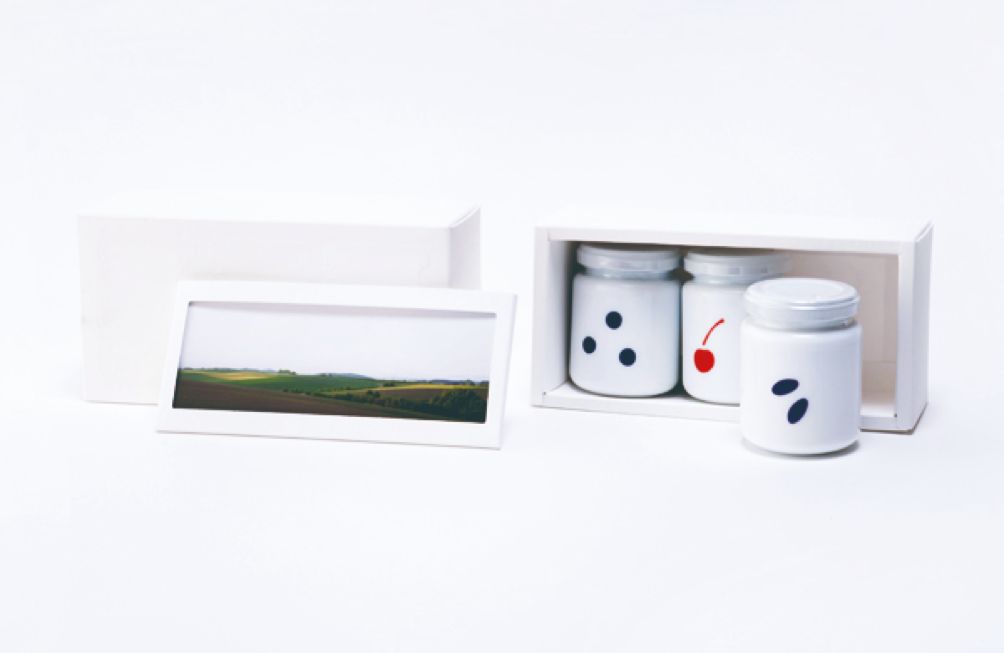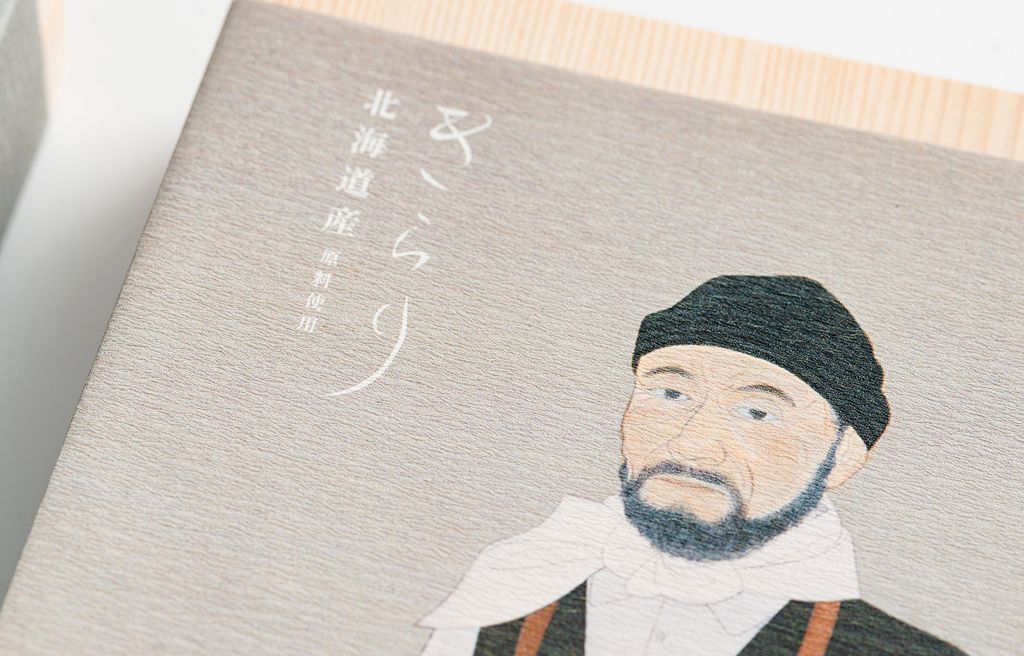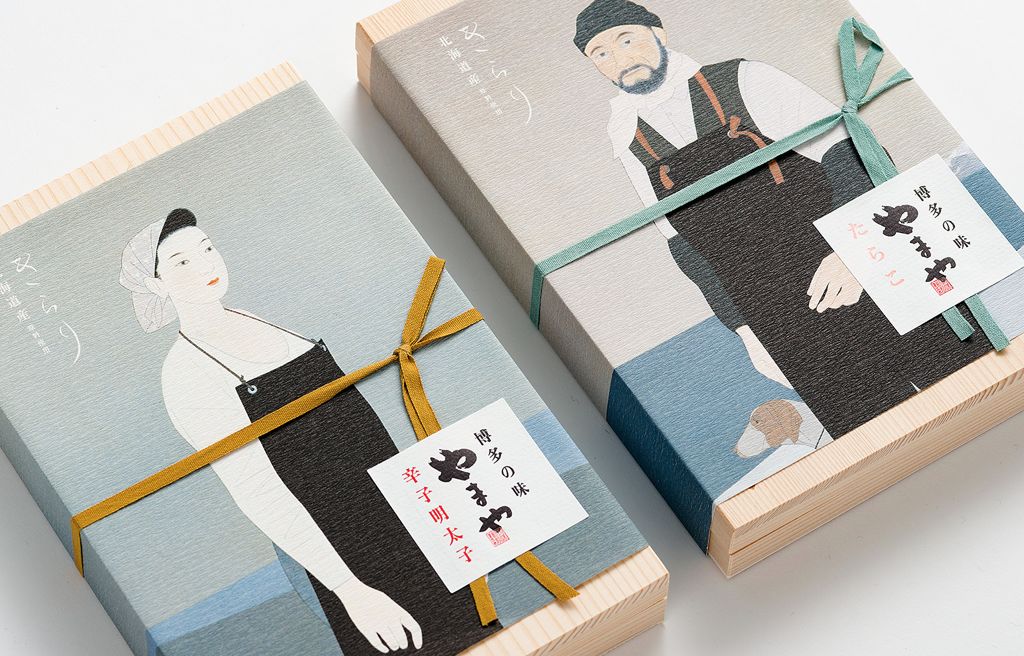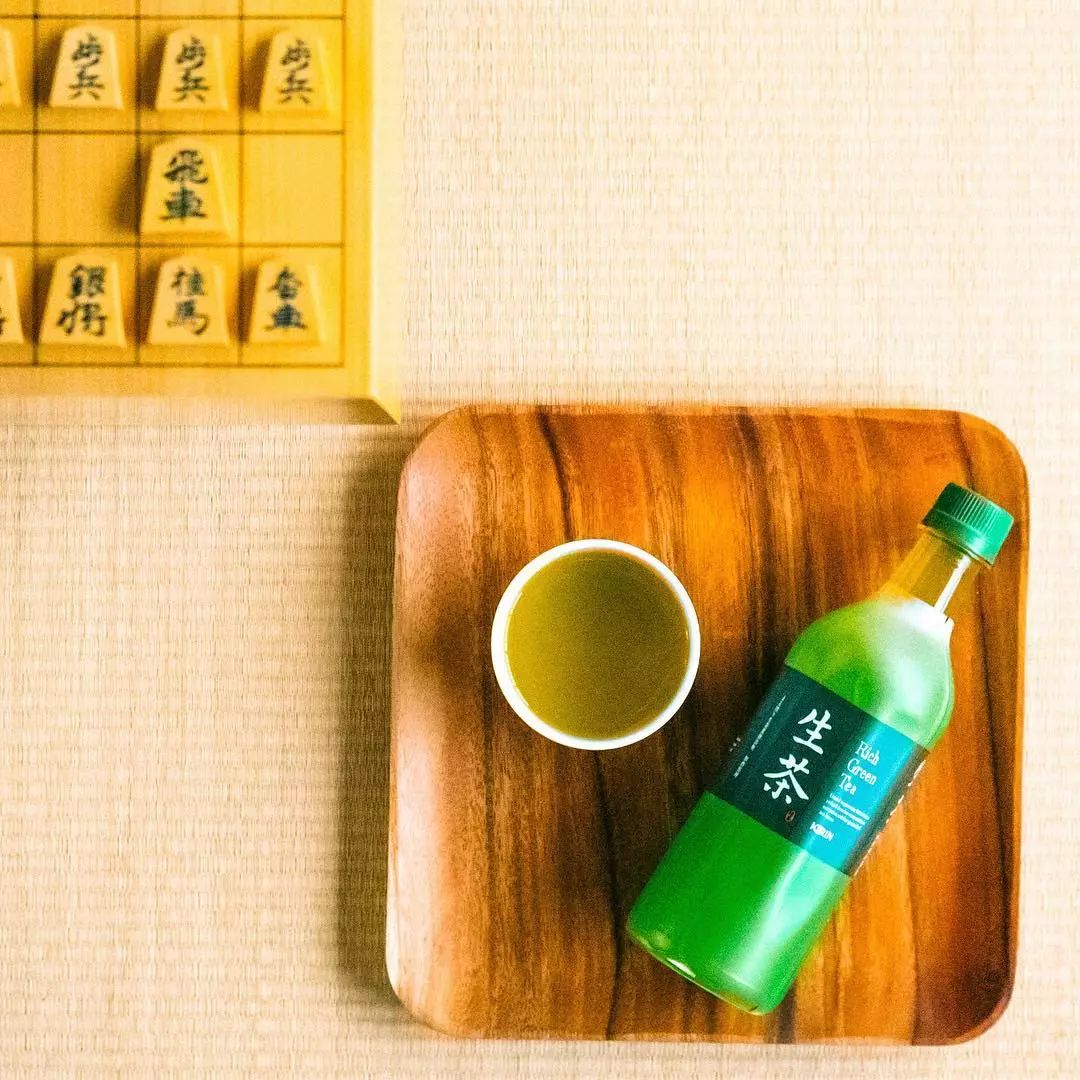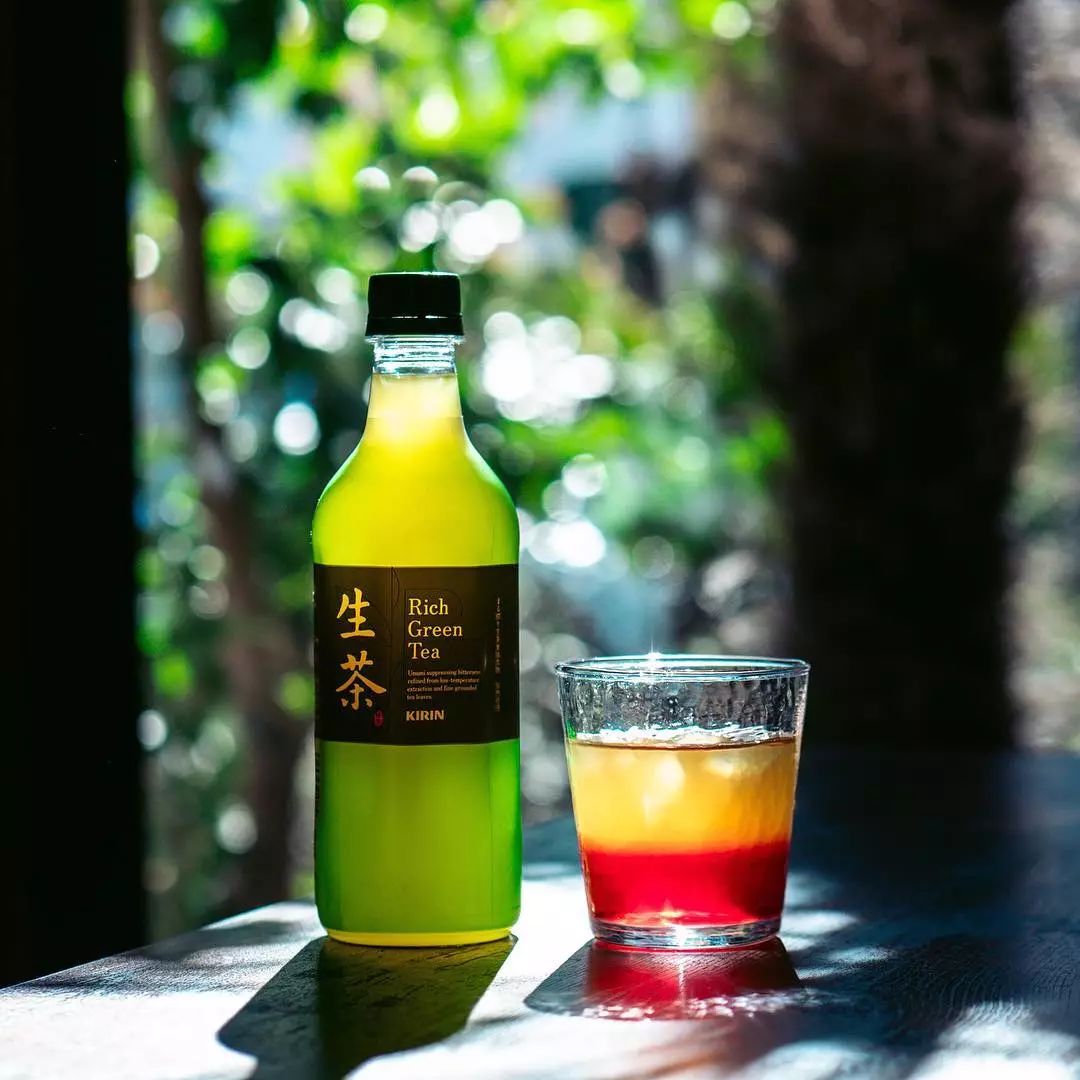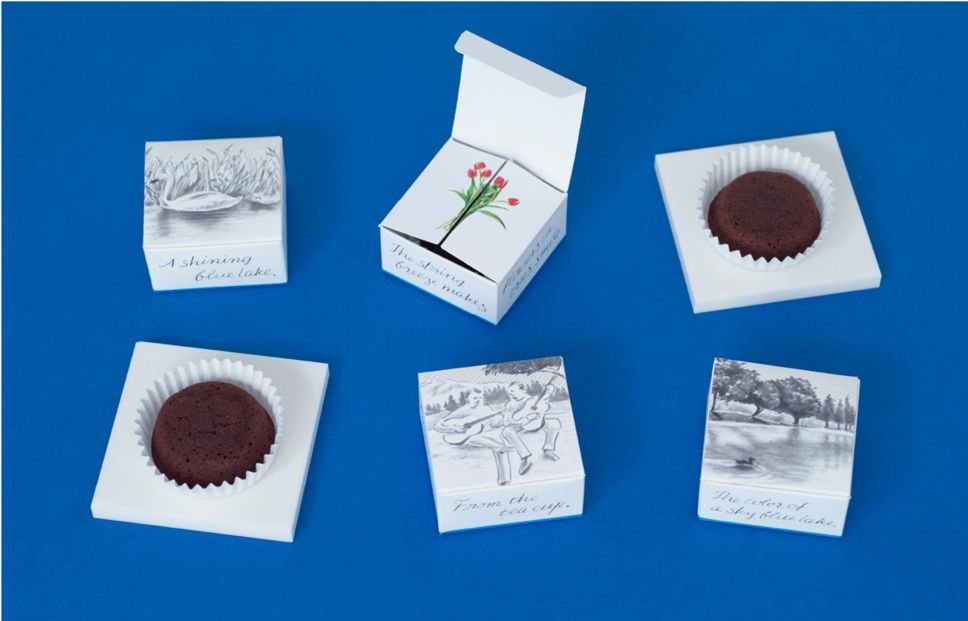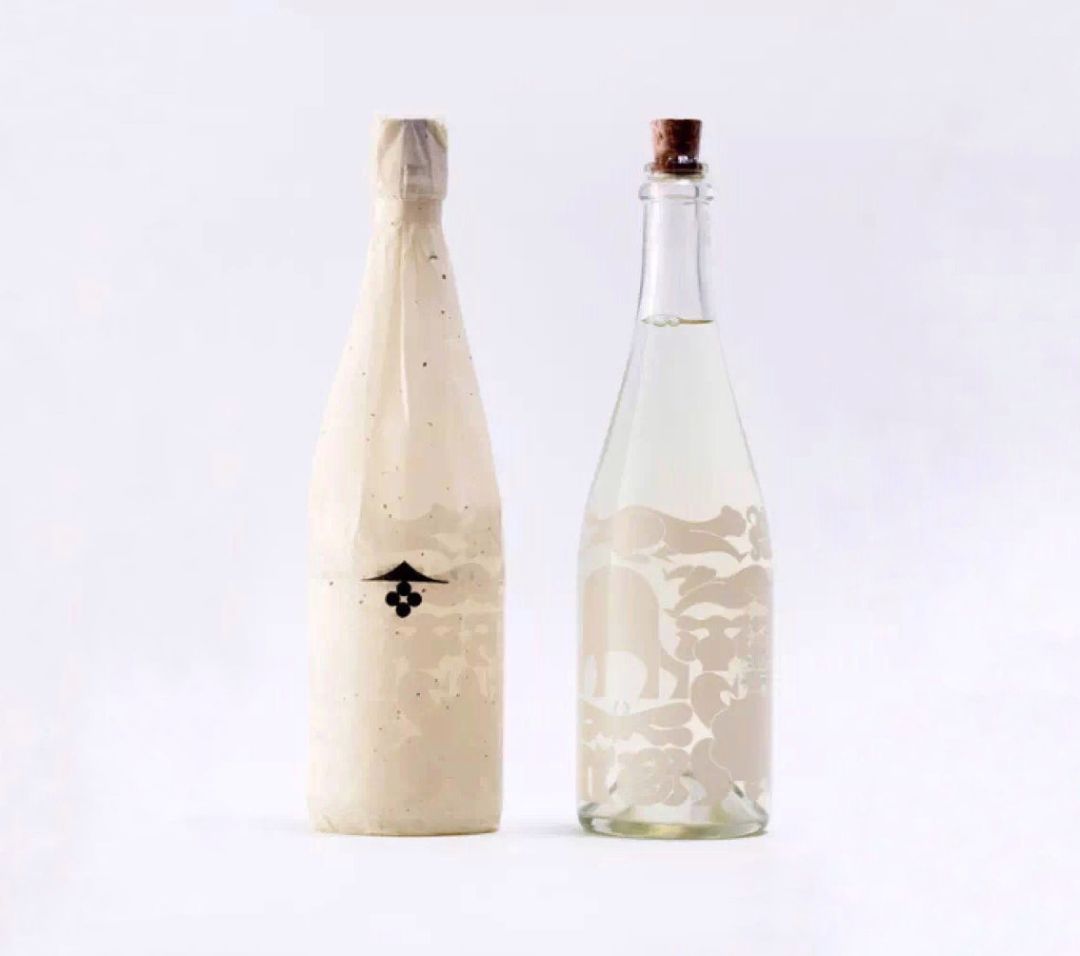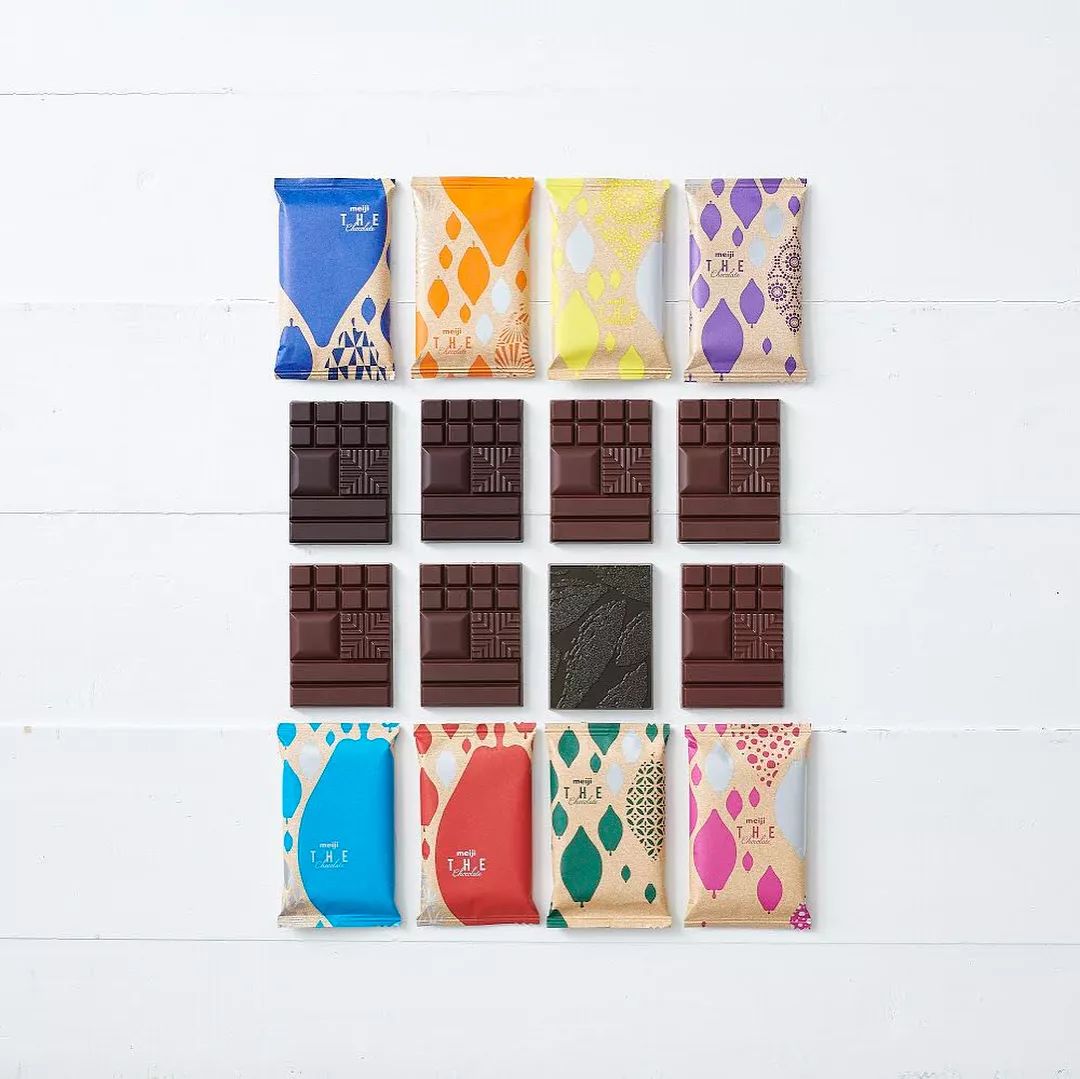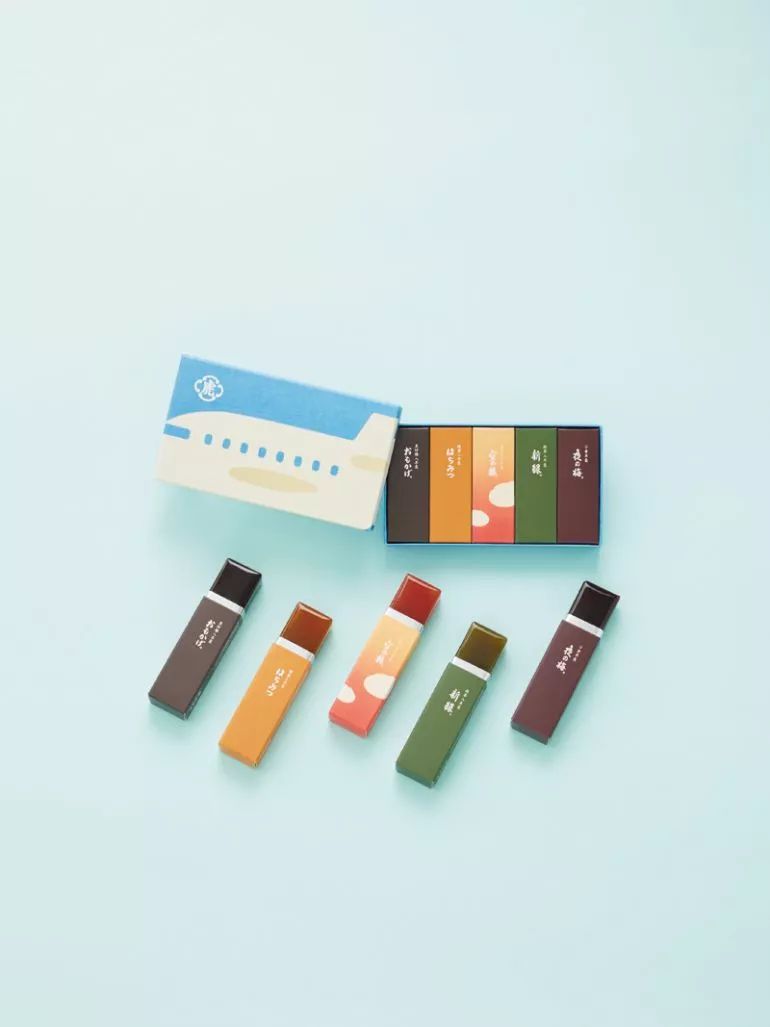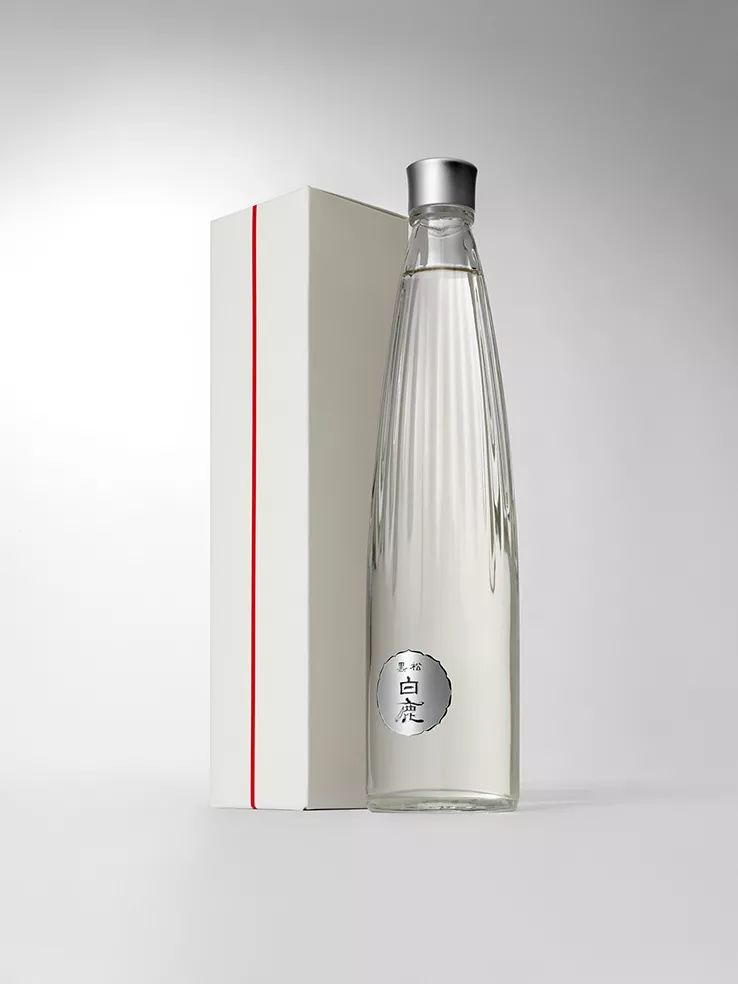
日本最美包装大赏:有些零食,负责好看就够了
说到小时候最爱的香菇肥牛和咪咪虾条,和咸咸淡淡的味道一起涌上心头的,往往还有外面那一层薄薄的包装。尽管我们被越来越多的物品包围,“包装”却是这个故事里不变的开端。一个足够美好的包装,不仅会道出商品的价值,打开它时窸窸窣窣的声音、光滑或粗糙的手感、视觉上的感触,更会化为记忆留存。
今天想和大家分享一个有关包装的大奖——1985年以来,日本包装设计协会(JPDA)每两年一次颁发设计大奖,奖励那些在商品过剩的年代里,脱颖而出的包装。让我们先从人人都爱的零食看起吧🍬
YAMAYA きらり辛子明太
2013
福冈的辣味明太子品牌Yamaya的招牌产品,精选北海道喷火湾的阿拉斯加鳕卵,属明太子中的上品。北海道的插画师蓬田康弘在包装上细致地描绘出了品牌创始人山本夫妇围着围裙的形象。
简洁的木盒和沉静的色调令人联想起大海,凸显出产品的鲜度和高级感,而插画又令人追忆起品牌的原点——来自一个日式家庭厨房的温暖心意。
美瑛果酱
2019
北海道美丽的农业之町美瑛出产的果酱,不同于大多数果酱“土特产风格”的包装,简洁的白色罐体敢于删去多余信息,这源于对果酱本身的品质足够自信,在吃完之后也有诸多循环使用的可能性。
而包装盒本身则变为相框——“本品建议搭配产地风景一并食用”。这款包装也获得了2018年的Good Design赏。
宝塚牛乳
2015
兵库县的人气牛奶屋宝塚的招牌包装,设计师植松达马从众多的红色中选出了不易过时的一种,配合圆乎乎的玻璃瓶,贴合我们小时候对牛奶的亲切记忆。
Logo仅仅是两个简洁的圆圈,以线条的细微变化唤起与生产者的联结,组成无添加、无调整牛奶的安心形象。
KIRIN 生茶
2017
遍地都是自动贩卖机的日本,茶类饮料更是战国中的战国,麒麟(KIRIN)却凭着2016年升级后的「生茶」脱颖而出。因为太火,甚至为此开出了专门的Ins账号。其中的秘诀除了低温萃取、抑制苦涩的好味道,更少不了设计上的功夫。
这款包装的设计指导福泽卓马是2018年JAGDA的新人赏得主(🔍点击回顾)。圆润的瓶子有哑光质感的表面,半透明的抹茶色衬托了茶汤的鲜度,减少了塑料瓶的“速食感”。因为这份简洁,反而老远就能自动售货机眼花缭乱的选项里辨别出来。
RURU MARY'S 巧克力
2019
巧克力集团Mary Chocolate的新品牌,包装由2016年JAGDA新人赏的获得者川上惠莉子操刀,在少女感和贵妇感之间取得了平衡。随着打开盒子,浅淡的素描风景里跃出花植的色彩,作为收尾的巧克力显得稳重又好吃😋
资生堂╳醉仙酒造 纯米大吟酿
2019
资生堂跨界做清酒?这样的说法并不全对。这款清酒源于资生堂2011年日本东山大地震后的复兴支援计划。资生堂的两位创意人——艺术总监广川MARIA和设计师小林一毅花了整整一年,为岩手县冰上山边的小酒坊「醉仙酒造」设计了这款包装,以此作为酒坊的新品牌「冰上四丸(氷上よんまる)」的出发点。
LOGO图案由手工盖章
它的关键词是“当地”。这一年里,设计团队在春夏秋冬都亲赴小镇生活,感受和观察变幻的风景,与农人和手工职人交流。最后的包装使用了本地出产的和纸,颜色和纹理经多次调整,希望尽可能地接近稻米本身的质感。玻璃瓶上的纹样来自当地山海中的生物,左上角的「冰上」字样取自附近冰上神社的牌匾。
虎屋 机场限定 迷你羊羹
2017
机场,往往是一次旅行中冲动消费的最后据点,自如地游走于时间的羊羹老铺虎屋给出了一个靠谱的选择——从2016年开始发售的机场限定迷你羊羹套装,内含虎屋经典的羊羹口味和机场限定的特别口味,无论是做伴手礼还是纪念品都让人舍不得吃啊!
店头的包装颜色随季节更换,夏季是蓝色的天空,冬季则是日落时的模样。由葛西薰担任设计指导,即使是现代图案也不失传统风情。(羽田/成田机场均有出售)
黑松白鹿 日本酒
(2013)
清酒和红酒比起来,好像总显得有些土气??为了打破这种印象,创立于1662年的清酒老牌黑松白鹿请龟仓雄策奖得主平野敬子设计了新包装。
打破暗色瓶子搭配巨大毛笔字的沉闷定式,经过切割的透明瓶身诚实地突出了清酒本身的质感,和银色标签搭配,如香水瓶一般简练时髦。相比传统清酒,也减少了容量,轻盈的瓶子主打即开即饮的新鲜度。
meji THE Chocolate
2019
百年历史的零食大户meji最近几年主打的系列,请来石原里美代言,一举创下了新品销售记录。
包装中间的部分以可可果实为原型,可被取下作为书签,不同的纹样和色彩意在强调这一系列的重点:对可可豆产国、甚至具体到农场的追本溯源。微妙的风味区别被印在了盒子背面,连内部巧克力方块的切割也提供了四种不同的品尝模式,呼应那句广告语:大人的舌头。
卡乐比 Potato Fritz
2019
我们都爱的网红零食卡乐比(代表作是薯条三兄弟和水果麦片)最拿手的土豆料理。这个新系列走自然路线,只有盐味(蓝色包装)和黄油(蓝色包装)两种经典口味。包装设计也以不易过时的“新定番”为目标,简洁的现代风格中透着淡淡的淳朴,除了很“小时候”的纹样和颜色,还因为字体长得和薯块本身很像吧。